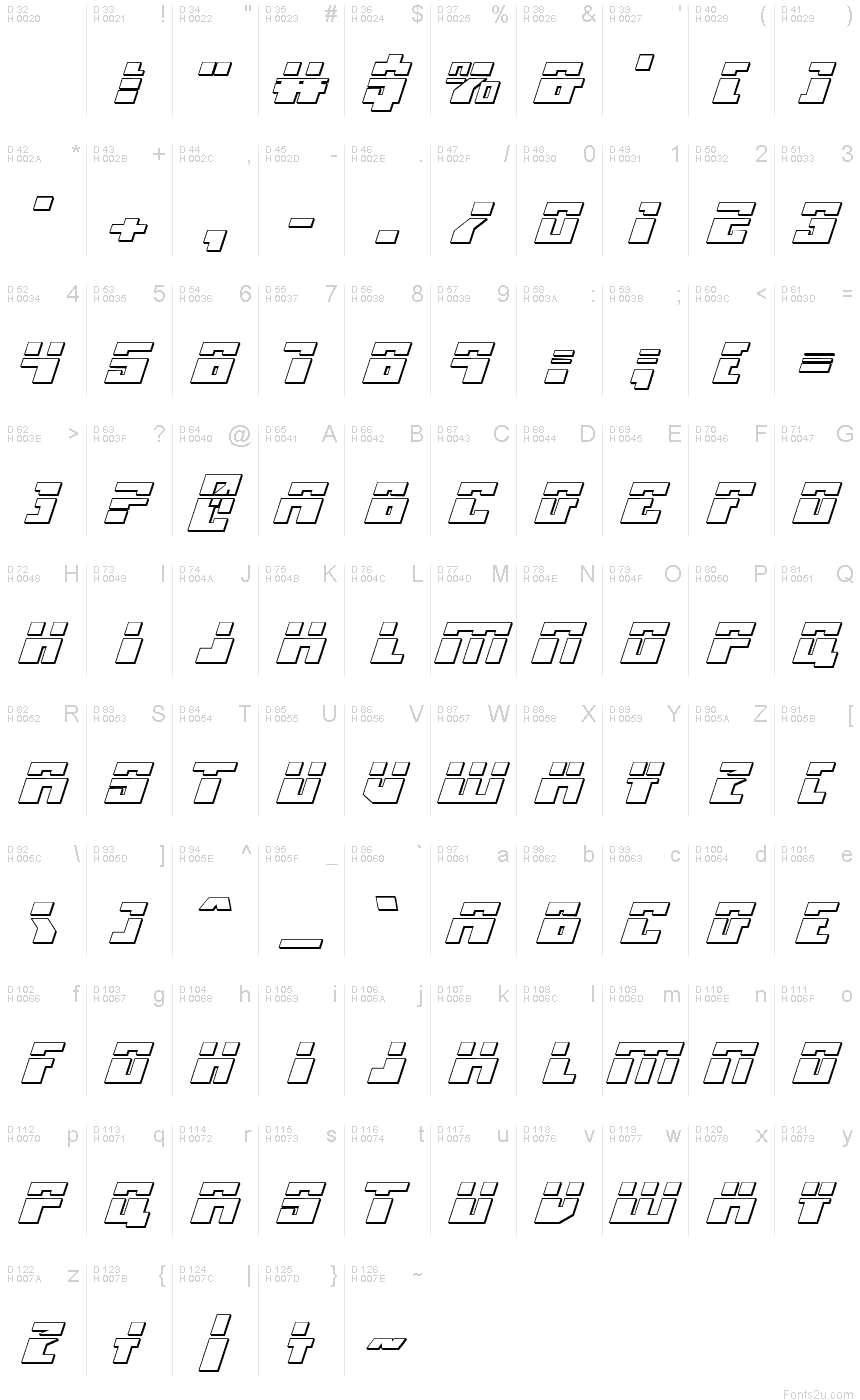
Micronian Laser 3D Italic von Iconian Fonts ist eine kostenlose, konturierte Techno-Display-Schrift mit starker Vorwärtsneigung, breiten, eckigen Formen und markanten horizontalen Einschnitten. Ihr doppelt liniertes Schriftbild erinnert an geschlitzte Maschinenpaneele.
Ein Science-Fiction-Spiel-Interface ist das überzeugendste Einsatzgebiet, bei dem die konturierten Buchstaben metallische Bedienelemente, Raumschiffmarkierungen und Industrie-Bildschirme widerspiegeln. Dasselbe technisierte Profil passt zu E-Sport-Branding und Postern für elektronische Musik mit Roboter- oder Space-Age-Thematik. Auf Merchandising-Artikeln und Spielverpackungen kann die Schrift eher Teil eines Raumschiffabzeichens oder einer technischen Dashboard-Grafik werden, als dass sie das Produkt lediglich benennt.
Micronian Laser 3D Italic